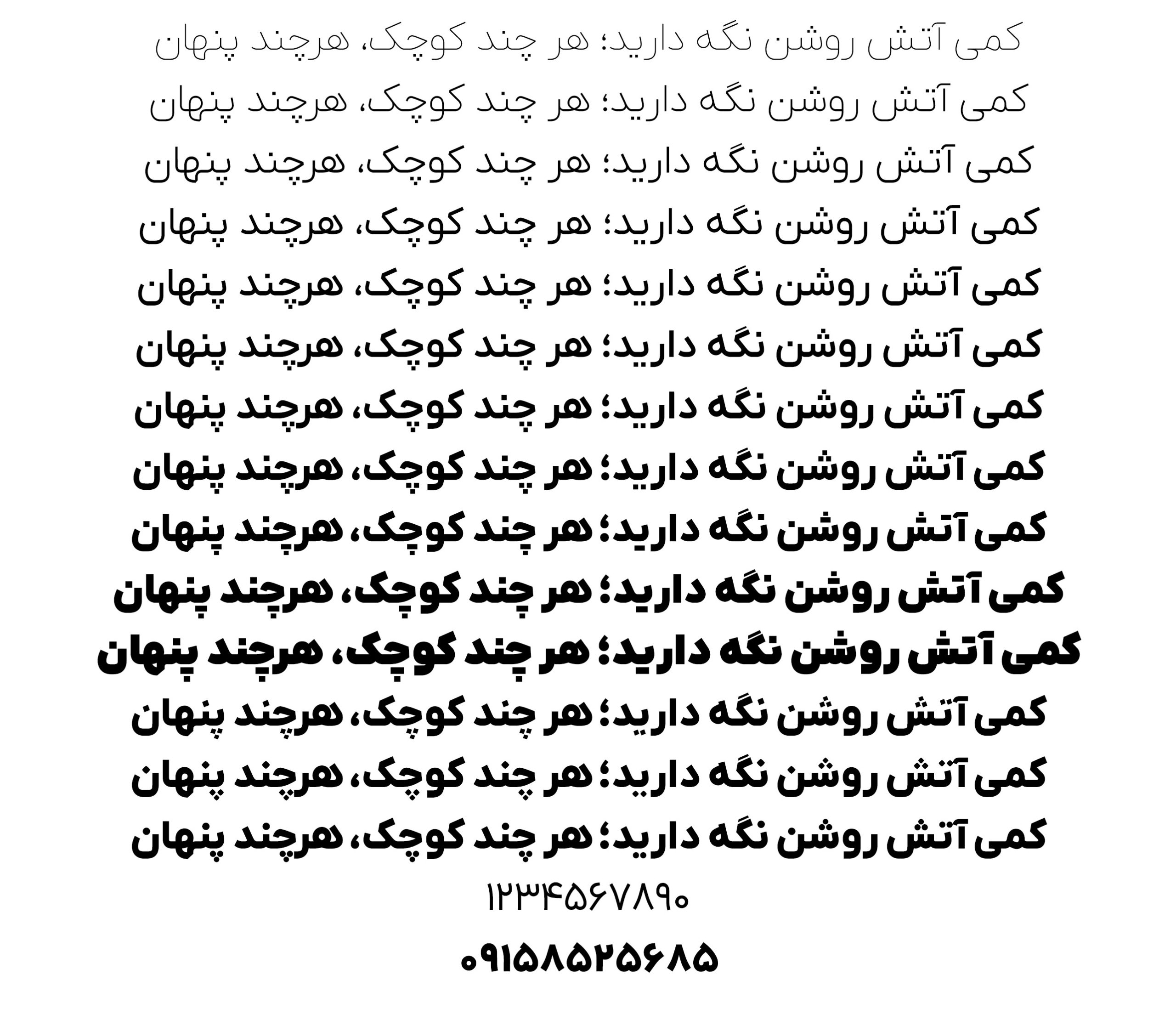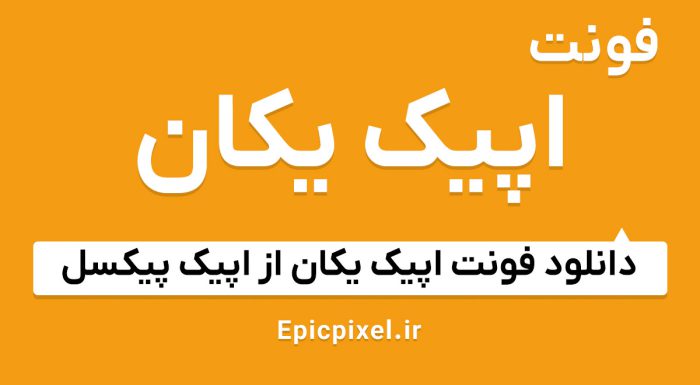
| ⭐ توضیحات | مجموعه ای کامل از فونت های اپیک یکان و نسخه شبیه سازی شده از ایران یکان
فونت اپیک یکان با پشتیبانی از حروف فارسی ، انگلیسی / لاتین ، اعداد فارسی Fu Num بهمرام نسخه متغییر وریبل Variable و نسخه وب ساده ، متغییر |
فونت اپیک یکان معرفی، تاریخچه و کاربردهای آن
معرفی فونت اپیک یکان
تعریف فونت و اهمیت آن در طراحی گرافیک
فونت به مجموعهای از حروف، علائم، شمارهها و سمبلهای مشابه همدسته شده با قالب خاص، با نام خود، که برای نمایش متن به کار میروند، گفته میشود. هر فونت دارای خصوصیات منحصر به فرد خود است که باعث میشود بین دیگر فونتها قابل تشخیص باشد. برخی از خصوصیات مشخص کننده فونت عبارتاند از: سایز، ضخامت، شکل، زاویه، فاصله، رنگ و غیره.
فونتها نقش بسزای در طراحی گرافیک دارند. طراح گرافیک با استفاده از فونتهای مناسب میتواند پیام خود را به صورت جذاب، خوانا و موثر به مخاطب انتقال دهد. فونتها میتوانند شخصیت، احساس، سبک و هویت طراحی را تعیین کنند. برای مثال، فونتهای سریف (Serif) معمولاً با جدیت، رسمیت و اعتبار همراه هستند، در حالی که فونتهای بدون سریف (Sans Serif) بیانگر سادگی، مدرنیته و خلاقیت هستند.
ویژگیها و خصوصیات فونت اپیک یکان
فونت اپیک یکان یکی از مشهورترین و پرکاربردترین فونتهای فارسی است که در بسیاری از زمینههای طراحی گرافیک به کار میرود. این فونت دارای ویژگیها و خصوصیات زیر است:
فونت اپیک یکان یک فونت بدون سریف است که دارای خطوط صاف و روان است.
فونت اپیک یکان دارای حروف بزرگ و کوچک است که باعث میشود تفاوت بین حروف اول و آخر کلمات را به خوبی نشان دهد.
فونت اپیک یکان دارای حروف با شکلهای منحصر به فرد و مشخص است که باعث میشود بین حروف مشابه مانند آ، د، ر، ز، ژ، س، ص، ض، ط، ظ تمایز قائل شود.
فونت اپیک یکان دارای حروف با ضخامتهای مختلف است که باعث میشود برای نمایش تأکید، عنوان، زیرعنوان و متن عادی از آنها استفاده شود.
فونت اپیک یکان دارای حروف با زاویههای مناسب است که باعث میشود جریان و رفتار حروف در جهات مختلف را نشان دهد.
فونت اپیک یکان دارای حروف با فاصلههای منطقی است که باعث میشود خوانایی و تعادل متن را حفظ کند.
کاربردهای فونت اپیک یکان X
استفاده از فونت اپیک یکان در برندینگ و تبلیغات
فونت اپیک یکان به دلیل داشتن شخصیت ملّی و هویت بخش، بسیار مناسب برای استفاده در برندینگ و تبلیغات است. بسیاری از برندها، سازمانها، موسسات و شرکتهای معروف و محبوب از فونت اپیک یکان برای طراحی لوگو، نماد، سربرگ، کارت ویزیت، بروشور، پوستر و غیره استفاده کردهاند.
فونت اپیک یکان به دلیل داشتن خطهای صاف و روان، خطهای بزرگ و کوچک، شکلهای منحصر به فرد، ضخامتهای مختلف، زاویههای مناسب و فاصلههای منطقی، بسیار مناسب برای استفاده در محصولات چاپی و دیجیتال است. این فونت باعث میشود محصولات چاپی و دیجیتال دارای جذابیت، خوانایی، تعادل، تناسب، هارمونی، تأثیرگذاری و حرفهای باشند. برخی از محصولات چاپی و دیجیتال که از فونت اپیک یکان استفاده میشود عبارتاند از:
کتابها، مجلات، روزنامهها، کاتالوگها، فلایرها، کارت پستالها، دعاييها، سررسیدها، تقدیرنامهها، گزارشها، رزومهها و غیره.
سایتها، بلاگها، پورتالها، خبرنامهها، اپلیکیشنها، بازیها، پرزنتیشنها، آمورشها، اینفوگرافیکها، پودکستها، ویدئوها و غیره.
استفاده از فونت اپیک یکان در سایتها و برنامههای کاربردی
فونت اپیک یکان به دلیل داشتن سبک مدرن و خلاق، سبک ساده و شفاف، سبک قابل تطبيق با هر زبان ديگري (Multilingual)، سبک قابل تطبيق با هر سايز و رزولوشن صفحه نمايش (Responsive)، سبک قابل تطبيق با هر سيستم عامل و مرورگر (Cross-Platform)، بسیار مناسب برای استفاده در سایتها و برنامههای کاربردی است. این فونت باعث میشود سایتها و برنامههای کاربردی دارای زیبایی، کارآمدی، کاربرپسندی، امنیت، سرعت و بهینهسازی باشند.
نکات مهم در استفاده از فونت اپیک یکان
رعایت قواعد تایپوگرافی و هماهنگی رنگها
فونت اپیک یکان یک فونت با کیفیت و حرفهای است که برای نمایش بهتر محتوا، نیاز به رعایت قواعد تایپوگرافی و هماهنگی رنگها دارد. برخی از این قواعد عبارتاند از:
انتخاب سایز مناسب برای حروف بزرگ و کوچک، عنوان، زیرعنوان و متن عادی
انتخاب ضخامت مناسب برای نشان دادن تأکید، تضاد، تغییر و جذابیت
انتخاب شکل مناسب برای نشان دادن جریان، حالت، معنا و مفهوم